Kiosko de Mantecón (Torrelavega)
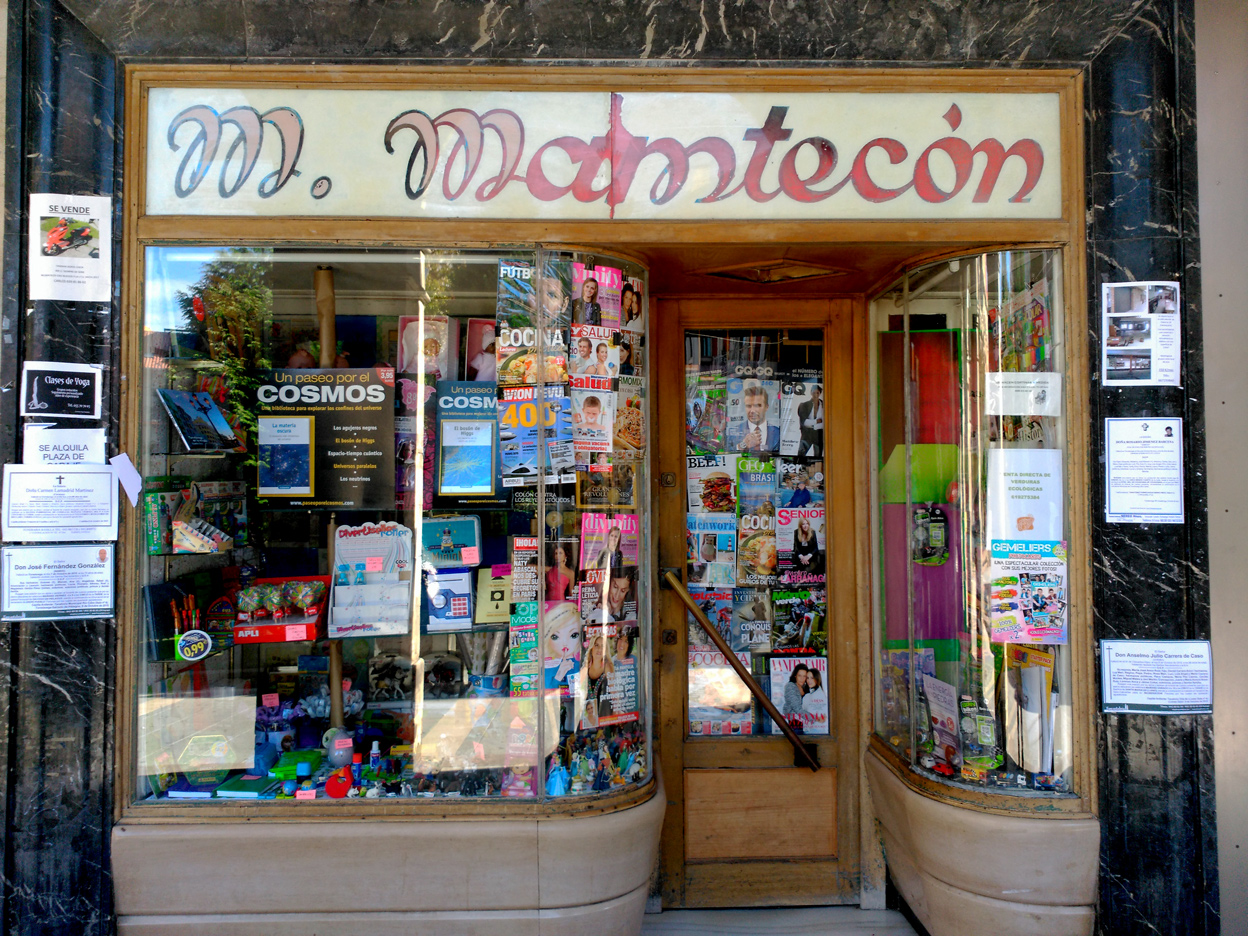
Si en la Capital del Besaya hay un comercio que tiene un encanto especial, es este. Sus vidrios curvos, mármoles y su rótulo con esa tipografía tan maravillosa han creado una imagen e identidad en la memoria colectiva de varias generaciones de Torrelavega.
Esperamos que podamos seguir disfrutando en los paseos por Torrelavega de ese iconografía tan emblemática, que ciertamente, se ha de proteger.